「推しにうちわを見つけてもらいたいけど…フォントってどう選べばいいの?」
そんな風に迷ったことはありませんか?
応援うちわの文字は、見た目の可愛さだけでなく「遠くからでも読みやすいか」がとっても大切。特にドームやアリーナなどの広い会場では、フォント選びが伝わる・伝わらないを大きく左右します。
私自身、初めてうちわを作ったとき「せっかくの気持ちが、伝わらなかったらどうしよう…」とすごく不安でした。でもフォントを変えるだけで、「あっ、ちゃんと目線が来た!」と感じられた瞬間があって。その体験から、文字って大事だなぁと実感しました。
この記事では、ライブ歴20年以上&うちわ制作も何度も経験してきた筆者が、「これは使いやすい!」と感じたおすすめフォントを、大人女子向けにやさしくご紹介していきます。
うちわ用フォントを選ぶときの3つのポイント
まずは、応援うちわにぴったりなフォントを選ぶうえで意識したいポイントを3つご紹介します。
実は、選ぶフォントによって、うちわの印象はガラッと変わります。かわいらしく見せたいのか、かっこよくアピールしたいのか――文字の形や太さによって、伝わり方にも違いが出てくるんです。
だからこそ、メッセージの内容や推しの雰囲気に合ったフォントを選ぶことが大切。見た目のおしゃれさだけでなく、“伝わりやすさ”も意識してみましょう◎
- 太くて線がはっきりしていること
細すぎる文字や装飾が多すぎるフォントは、遠くから見ると読みにくくなってしまいます。太字で輪郭がくっきりしているものを選ぶのがポイント。 - ひらがな・カタカナも可読性が高いこと
名前や「ピースして」「指さして」などのメッセージには、ひらがな・カタカナが多く使われます。日本語に対応しているフォントで、読みやすさを確認しておきましょう。 - 推しの雰囲気に合っていること
王子様系ならかっこいい系、癒し系ならやわらかフォントなど、推しのキャラクターやグループの雰囲気に合ったテイストを選ぶと、気持ちがより伝わります。
初心者さんにも安心!うちわにおすすめのフォント10選
ここでは、無料で使えるものを中心に、推し活女子に人気のフォントを10個ピックアップしました。
実際にライブうちわでよく使われている定番フォントから、見た目もかわいくて扱いやすいものまで、初心者さんでも安心して選べるラインナップになっています。
「この文字、見やすいな」「この雰囲気、推しにぴったりかも」と感じたら、ぜひ実際のうちわ作りにも活用してみてくださいね◎
やさしさゴシック
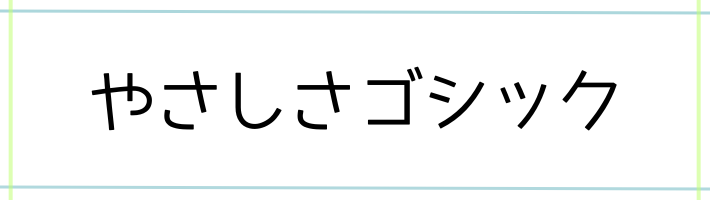
丸みがあって親しみやすい、王道の定番フォント。太さもちょうどよく、うちわ文字にぴったりです。
やさしく呼びかけたいときや、推しの名前を可愛く目立たせたいときにおすすめ。とくに“ふんわり系・癒し系”の推しや、やわらかい雰囲気のメッセージ(例:「ピースして」「にこにこして」など)と相性◎
カラフルな背景や推しカラーとの組み合わせでも、主張しすぎず自然に馴染んでくれます。シンプルだけど伝わる、万能型フォントです。
コーポレート・ロゴ丸
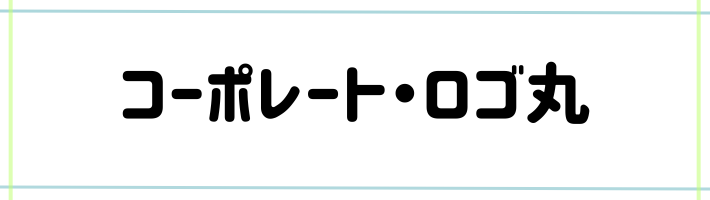
角が丸く、やわらかさを感じるフォントながら、線の太さがしっかりしていて読みやすさも抜群。
大人っぽさと可愛さをちょうどよく兼ね備えています。
「ちょうだいポーズして」や「手をふって」など、ほんのり可愛さを伝えたいメッセージにぴったり。どの推しタイプにも合わせやすく、落ち着いた雰囲気のうちわを作りたい方にもおすすめです。
背景が濃いカラーでもしっかり文字が映えるので、推し色×白文字×コーポレート・ロゴ丸の組み合わせはとても使いやすく、初心者さんにも安心です。
ラノベPOP
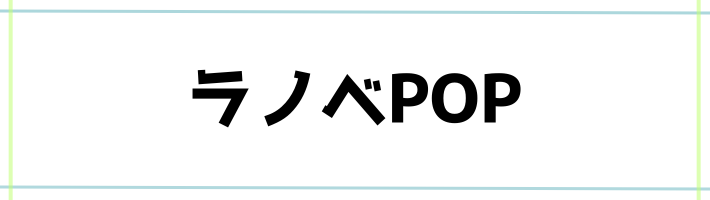
アニメのタイトル風で、インパクト抜群のフォント。
線が太くて角もシャープなデザインなので、遠くからでも視認性が高く、ライブ会場でも目立ちやすいのが特長です。
力強く伝えたいメッセージ(例:「指さして!」「見つけて!」など)や、ビジュアル系・元気系・かっこいい系の推しにとくにおすすめ。
ブラック地にネオンカラーの組み合わせとも相性が良く、ジャニーズのスタエン系ユニットやK-POP系など“映えを狙いたい”方にぴったりなフォントです。
ほのか明朝
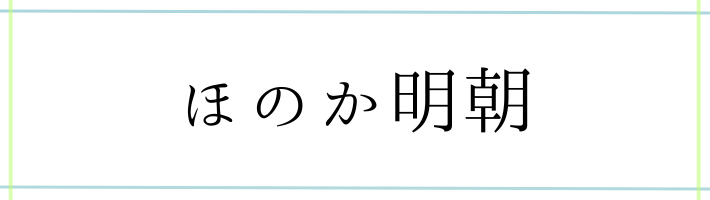
明朝体の持つ上品さの中に、ほんのりとやさしさがにじむフォント。
角がとがりすぎず、文字のバランスも美しいため、大人っぽくかわいらしい印象に仕上がります。
メッセージうちわにも向いていて、「ありがとう」「笑って」などの気持ちを伝える言葉を、丁寧に届けたいときにおすすめ。
癒し系・文化系の推しや、落ち着いたトーンでまとめたいときにぴったり。背景や装飾を控えめにして、文字そのものを主役にしたいデザインにも◎
コーポレート・ロゴB
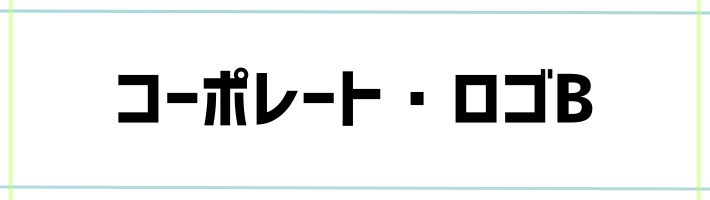
カクッとしたエッジの効いた太字が印象的で、読みやすさと安定感を兼ね備えたフォント。
力強く引き締まったデザインなので、ライブうちわにもしっかり映えます。
男らしい雰囲気のある推しや、スタイリッシュなグループ、クール系ユニットにぴったり。「かっこいい!」「指さして!」など、勢いのあるメッセージとも相性◎
背景が暗めの色でも埋もれにくく、白文字で使えばシンプルながらも存在感抜群。かっこよく決めたい大人女子の推し活におすすめの一本です。
ふい字
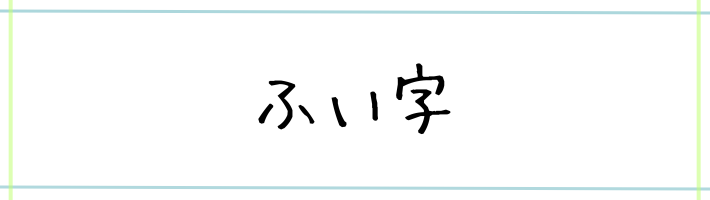
やさしい手書き風のフォントで、親しみやすさが魅力。クセが少なくナチュラルな印象なので、気取りすぎず、等身大の想いを届けたいときにぴったりです。
「大好きだよ」「応援してるよ」など、やわらかいメッセージ系うちわにおすすめ。アイドル系はもちろん、俳優さんやアーティスト系の推しにも自然に馴染みます。
装飾をシンプルにまとめても、手書き感がぬくもりをプラスしてくれるので、初心者さんにも扱いやすい万能フォントです。
JKゴシックL
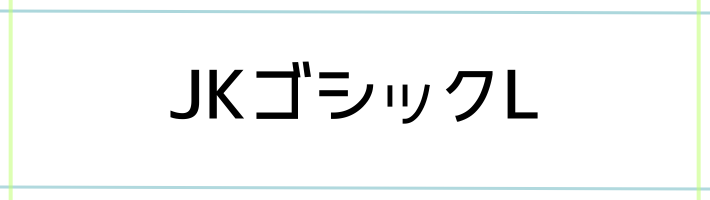
クセがなく、どんなデザインにもなじみやすいシンプルなゴシック体。
線の太さもちょうどよく、遠くからでも文字がくっきり見えるため、ライブうちわにとても人気のある定番フォントです。
特にSTARTO(旧ジャニーズ)系の現場ではよく見かけるフォントで、名前うちわ・メッセージうちわどちらにも対応しやすい万能型。初めてのうちわ作りでも「これなら安心」と思える仕上がりになります。
「こっち見て」「ピースして」などの定番フレーズとの相性も抜群。フォントで迷ったらまず選びたい、シンプルで伝わりやすい一文字です。
けいふぉんと!
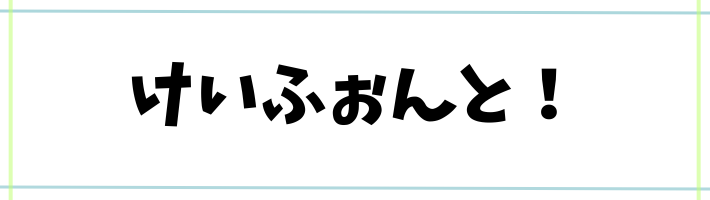
丸みのある線と、ゆるっとした手書き感が魅力のフォント。
かわいらしさがありつつも読みやすさはしっかり確保されていて、「ゆるふわ推し活」にぴったりのテイストです。
やさしく甘めの雰囲気を出したいときや、「笑って」「にこにこして」など、ほんわか系のメッセージにおすすめ。文字だけでもやわらかい印象になるので、装飾が少なめのうちわでも十分可愛く仕上がります。
とくにふんわり系のビジュアル担当や、癒し系の推しに使うと雰囲気がぴったり。スタエン系でも“かわいい”を押し出したいときに選びたいフォントです。
ロゴたいぷゴシック
どっしりと太く、直線的なラインが特徴のインパクト系フォント。
名前を大きく目立たせたいときに強い味方になってくれます。
ドームやスタジアムなどの広い会場でも埋もれにくく、視認性抜群。とくに「うちわを見てもらいたい!」「存在感を出したい!」という方におすすめです。
クール系や元気系の推しにもマッチしやすく、背景や装飾をシンプルにしても十分目立ちます。太めで重心が安定しているため、初心者でも配置しやすいのも魅力です。
ニコモジ+
丸ゴシック系の中でも、ほどよく丸みがありつつも視認性が高い、親しみやすい印象のフォント。文字のバランスがとても整っていて、やさしくて丁寧な雰囲気を演出できます。
推しに話しかけるようなフレーズや、やわらかいお願いメッセージ(例:「見つけてくれたらうれしいな」「手を振ってね」など)にぴったり。強すぎず、でもきちんと伝わる、そんな絶妙な存在感です。
カラーの組み合わせ次第で可愛くもかっこよくも使えるので、初心者さんでもアレンジしやすい万能フォントです。
推しに伝わる文字はこれ!うちわフォント比較ギャラリー4
| やさしさゴシック | ラノベPOP | ほのか明朝 | コーポレート・ロゴB | ふい字 |
| JKゴシックL | けいふぉんと! | ロゴたいぷゴシック | ニコモジ+ | コーポレート・ロゴ丸 |
推しのタイプ別!おすすめフォント組み合わせガイド
「どれを選んだらいいか分からない…」という方は、推しのタイプ別に選んでみるのもおすすめです。
推しのキャラクターや雰囲気に合わせてフォントを選ぶことで、うちわ全体の世界観がまとまりやすくなります。「王子様系ならきっちりした感じ」「癒し系ならやわらかい感じ」など、なんとなくでもイメージが湧いてきたら、自然とフォントも選びやすくなりますよ◎
| タイプ | おすすめフォント |
|---|---|
| 王子様・王道アイドル系 | やさしさゴシック / JKゴシックL / けいふぉんと! |
| クール・男らしい系 | ラノベPOP / コーポレート・ロゴB / ロゴたいぷゴシック |
| 癒し・ゆるふわ系 | ほのか明朝 / ふい字 / ニコモジ+ |
フォント選びも“推し活の一部”として楽しもう
うちわのフォントを選ぶ時間は、「どうすれば気持ちが届くかな」「どんな雰囲気が似合うかな」と、推しを想う大切なひととき。
読みやすくて、あなたらしさも伝わるフォントを選べば、ライブ当日がもっと特別な時間になるはずです。
気負わず、楽しみながら。うちわづくりも、ゆるっと推し活の一部として楽しんでいきましょうね♪